02 marca 2013 zaprezentowano TransType 4 for Mac, przyjazną aplikację do organizowania i konwersji fontów. Naprawisz oraz dostosujesz nazewnictwo i style dla całych rodzin fontów, utworzysz format TrueType z dowolnego formatu wyjściowego, np. VFB czy UFO. Zastosujesz ciekawe efekty do fontów. Przeprojektowano interfejs użytkownika. Teraz jest już pełne wsparcie dla webfontów: WOFF, EOT i SVG!
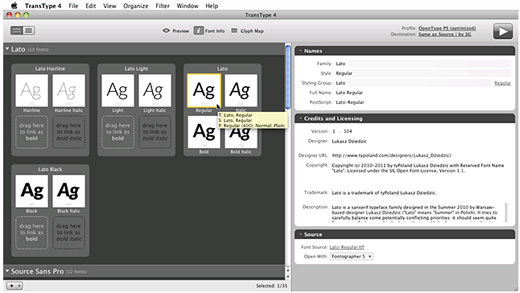
Łatwa konwersja fontów
Aplikacja TransType miała swój początek w czasach „fontowych wojen”, gdy producenci systemów operacyjnych walczyli chcąc narzucić formaty fontów. Każdy, kto pracował z fontami potrzebował TransType’a, aby szybko i łatwo dokonać konwersji pomiędzy różnymi formatami i platformami. W końcu wybrano wspólny format OpenType.
Teraz jednak mamy nowe formaty fontów, które są wykorzystywane w Internecie (WOFF, EOT, SVG) oraz te używane przez twórców fontów (UFO, VFB), więc potrzeba konwersji formatów jest nadal silna. Nadal ma znaczenie, czy fonty OpenType są typu PostScript czy TrueType (TTF lub OTF). Również pewna liczba starszych formatów PostScript Type 1 nadal istnieje, co sprawia, że trudno się poruszać z dokumentami między Mac OS X i Windows. Tutaj z pomocą przychodzi TransType 4, który obsługuje wszystkie te formaty (nowe i stare) i sprawia, że konwersja między nimi jest łatwiejsza niż kiedykolwiek wcześniej.
Zmniejszyć problemy z organizacją rodziny fontów
Jednym z największych kłopotów przy konwersji fontów między platformami zawsze była niezgodność struktury rodzin fontów i systemów nazewnictwa w różnych systemach operacyjnych. W wyniku tego, fonty mają około tuzina różnych pól i ustawień dotyczących nazewnictwa, które kontrolują w jaki sposób pojawiają się one w menu aplikacj. Zapewnienie, że pola te są zgodne z różnymi specyfikacjami i wytycznymi narzuconymi przez OS i producentów aplikacji i że są spójne w obrębie rodziny fontów, zawsze było koszmarem dla dostawców fontów, a szczególnie początkujących projektantów i artystów.
Aplikacja TransType 4 jest pierwszą na rynku, która niemal eliminuje ten problem, wprowadzając rewolucyjne, wizualne i intuicyjne podejście do zarządzania rodzinami fontów. Wszystko, co musisz zrobić, to polecić aplikacji TransType, aby wykonała optymalizację styli, a wszystkie fonty będą starannie zorganizowane w rodziny. Aby dokonać korekty wystarczy przeciągnąć kilka miniaturek reprezentujących pliki fonotowe lub kliknąć aby edytować jedno lub więcej pól tekstowych – i tak uzyskasz pewność, że fonty będą działać na różnych platformach.
Czas potrzebny, aby zamienić każdy projekt w formacie VFB lub UFO lub dowolne inny fonty jakie posiadasz na rodzinę fontów, tak aby działały we wszystkich systemach operacyjnych oraz we wszystkich przeglądarkach – z aplikacją TransType 4 dosłownie redukuję się z godzin do minut.
Możesz być bardziej kreatywny pracując z fontami
Fonty nie są po to, aby sprawiać kłopoty – są one przede wszystkim elementem kreatywności i zabawy. Dlatego aplikacja TransType 4 zawiera szereg zaawansowanych filtrów, które mogą zmianiać wygląd fontów. Niektóre z nich są czysto funkcjonalne. Np. filtr Blend pozwala wybrać dowolne dwa fonty i stworzyć nowy styl, który wygląda trochę jak każdy z fontów bazowych – idealny do tworzenia stylu medium w rodzinie, w której regular jest zbyt lekki, a bold jest zbyt ciężki. Filtr Tracking po prostu dodaje lub usuwa przestrzeń między znakami i wpisuje te zmiany w nowy font. Inne filtry są znacznie bardziej eksperymentalne – Blur lub Distort doda trochę swobodnego wyglądu do najbardziej korporacyjnych fontów bezszeryfowych, podczas gdy Round doda ciepła do najchłodniejszych form „techno” poprzez zmiękczenie jego kanciastych kształtów. Filtry nie zastąpią profesjonalnej pracy projektanta fontów, ale dają dużo satysfakcji przy ich stosowaniu.
Co TransType 4 może zrobić dla Ciebie
Dla domów wydawniczych lub projektantów fontów, którzy lubią twórczy proces projektowania krojów oraz chcą tworzyć fonty w formacie OpenType lub webowym, ale nie chcą borykać się z ich technicznymi szczegółami – TransType 4 jest idealnym towarzyszem dla głównego narzędzia, czy jest to FontLab Studio, Fontographer, TypeTool czy taki, który obsługuje formaty UFO (np. RoboFont, Glyphs lub FontForge).
Dla profesjonalnych grafików i dyrektorów artystycznych – TransType 4 może pomóc im eksperymentować z ich kolekcjami krojów pisma, dostosowując wagę fontu, jego kąt nachylenia lub trwale zmieniając odstępy między znakami.
Dla zwykłych użytkowników fontów – jeśli mają kłopoty z platformami czy niezgodności dotyczące aplikacji , TransType 4 pozwala rozwiązać te problemy. Również jeśli jesteś po prostu znudzony posiadanymi fontami, możesz czasami spróbować stworzyć nowe bardziej ciekawe.